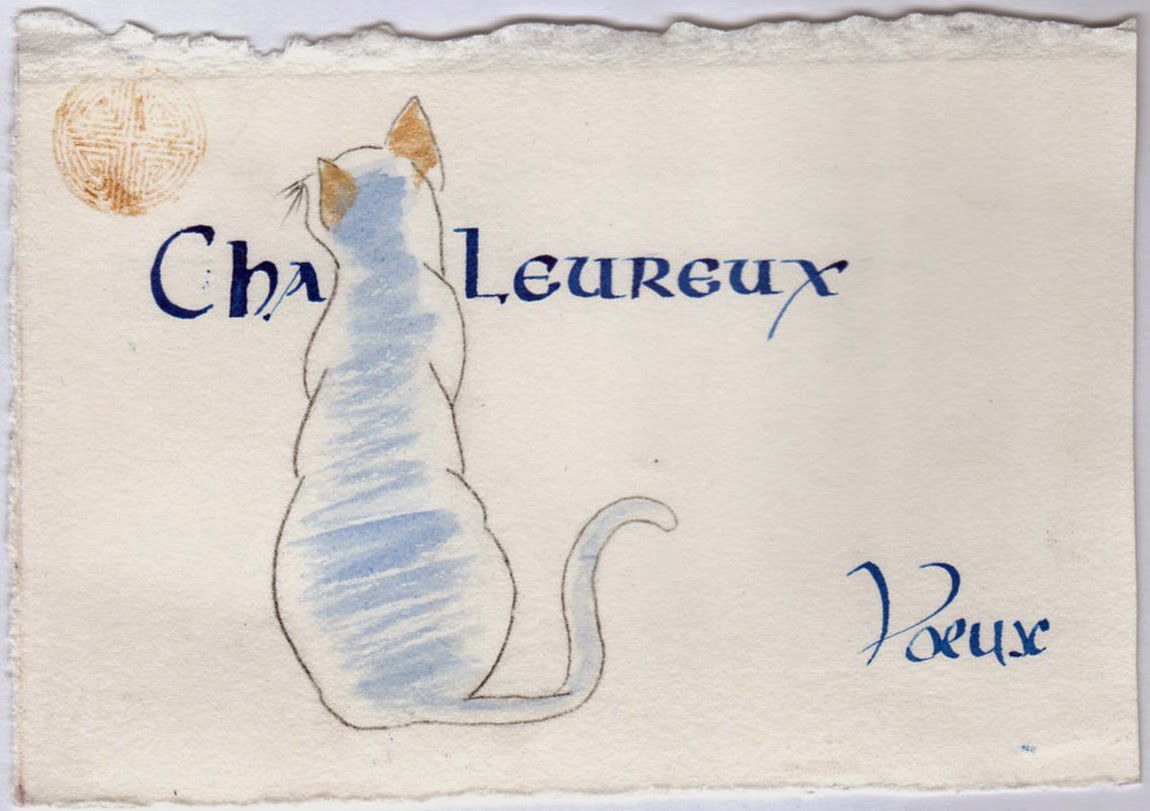
Mi-Novembre, j'ai participé à un stage Apex intitulé " Pinceau pointu et autres facéties... ".
Nous devions apporter des pinceaux type Pentel : en voici quelques modèles ci-dessous.
Bruno utilise le dernier modèle afin de pouvoir changer de médium et de couleur autant qu'il le souhaite et qu'il trouve plus agréable et plus performant !
Pour ma part, j'ai utilisé les 2 premiers et plus particulièrement le Pentel Color Brush (c'est ce que j'avais en stock... mais depuis, je me suis procuré l'autre !).
On a débuté par des exercices pour se mettre l'instrument en main... puis progressivement, nous avons essayé de faire des tracés avec de largeurs très différentes (extrême finesse à maxi-largeur) et enfin, pour certains, nous avons testé l'anglaise au pinceau pointu.
Le dimanche, Bruno nous a proposé de s'écarter de l'anglaise pour produire une calligraphie gestuelle en s'aidant de son modèle sans chercher à avoir une lisibilité parfaite.
Mes réalisations sont loin d'être parfaites mais je suis assez contente du résultat.
Mais les démonstrations de Bruno (qui est passé auprès de chacun de nous très régulièrement et montré comment améliorer nos traits) sont vraiment d'un tout autre niveau !